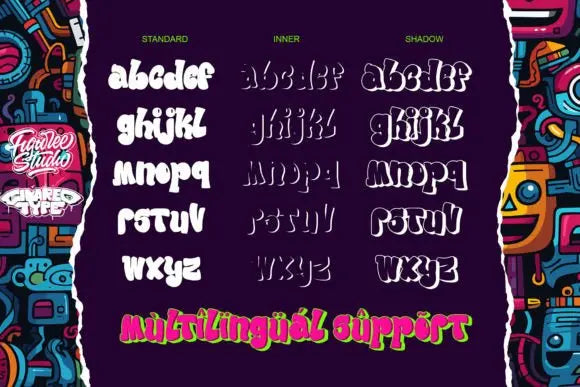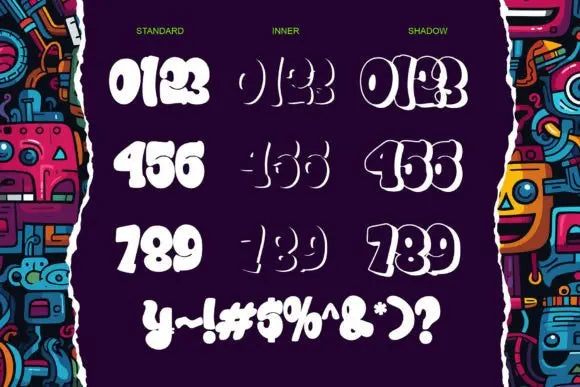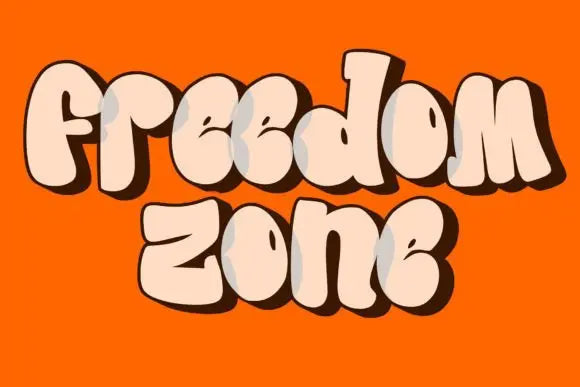
Fuente Urban Maxim
Urban Maxim” es una fuente de graffiti que presenta tres capas diferentes: sólida, sombra y sombra interior. Al utilizar esta combinación de capas en su diseño, puede crear un efecto tridimensional (3D) en su texto.
Fuentes como esta se utilizan a menudo en arte callejero, carteles u otros diseños que tienen como objetivo agregar profundidad y dimensión a su tipografía.
Con "Urban Maxim", tienes la flexibilidad de crear texto que se vea distinto y más pronunciado mediante el uso de las distintas capas. Esto le permite personalizar la apariencia de su texto para que se ajuste a la estética de su diseño.